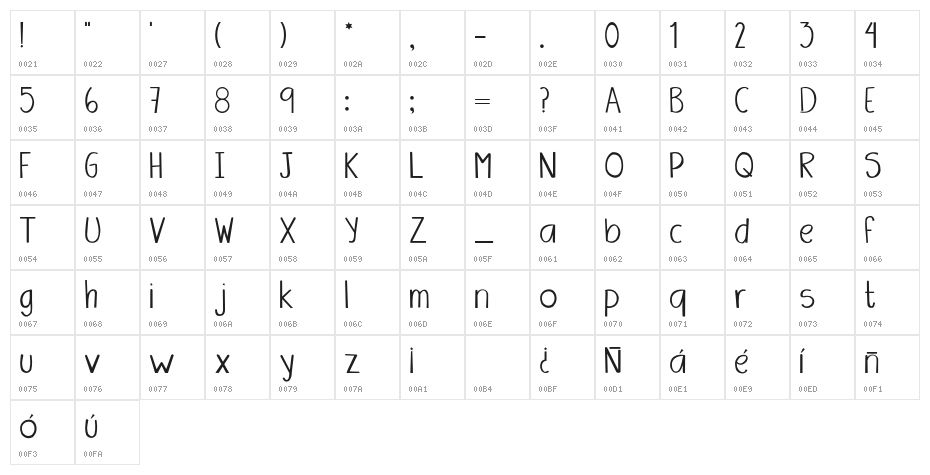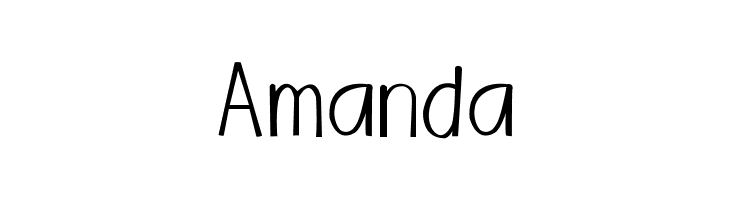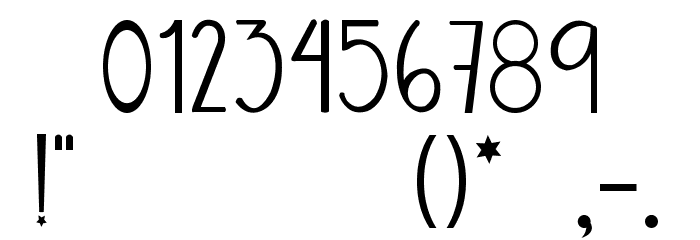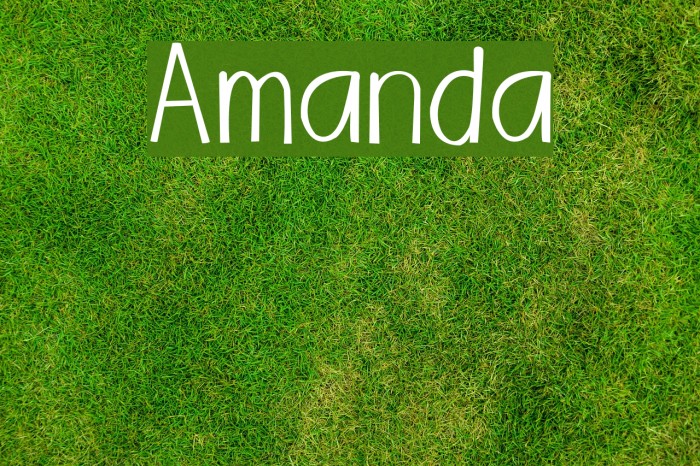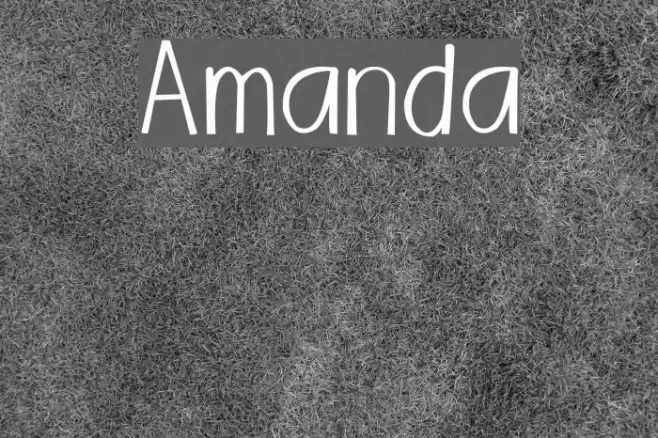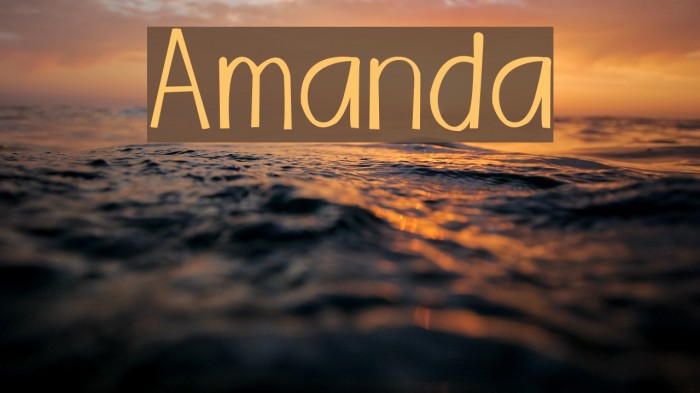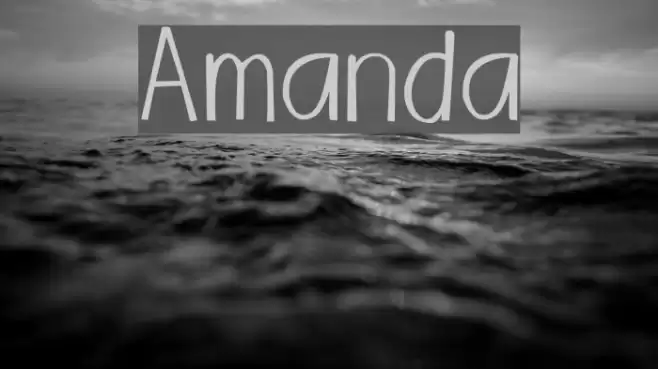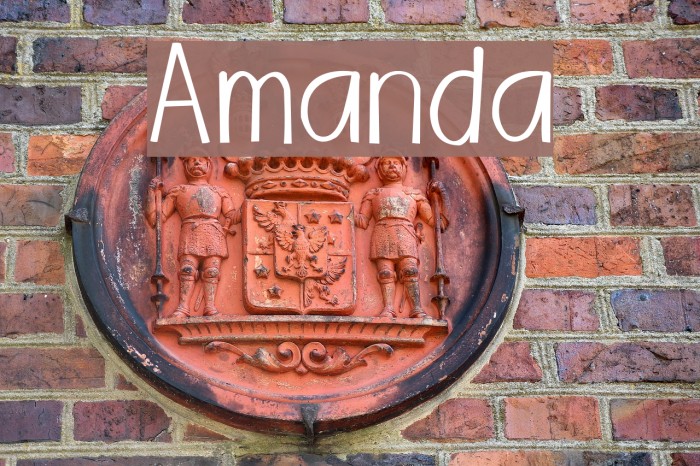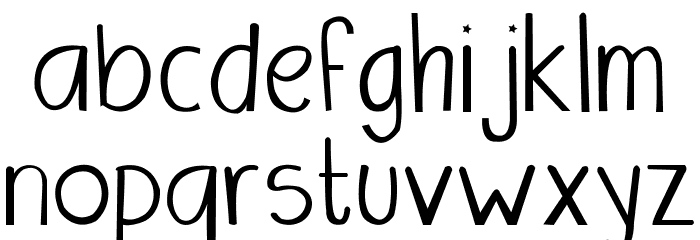
Amanda Font
| Gesamtstil | Playful |
| Vorgeschlagene Projekte | Ideal for children's books, greeting cards, playful branding, and creative posters. |